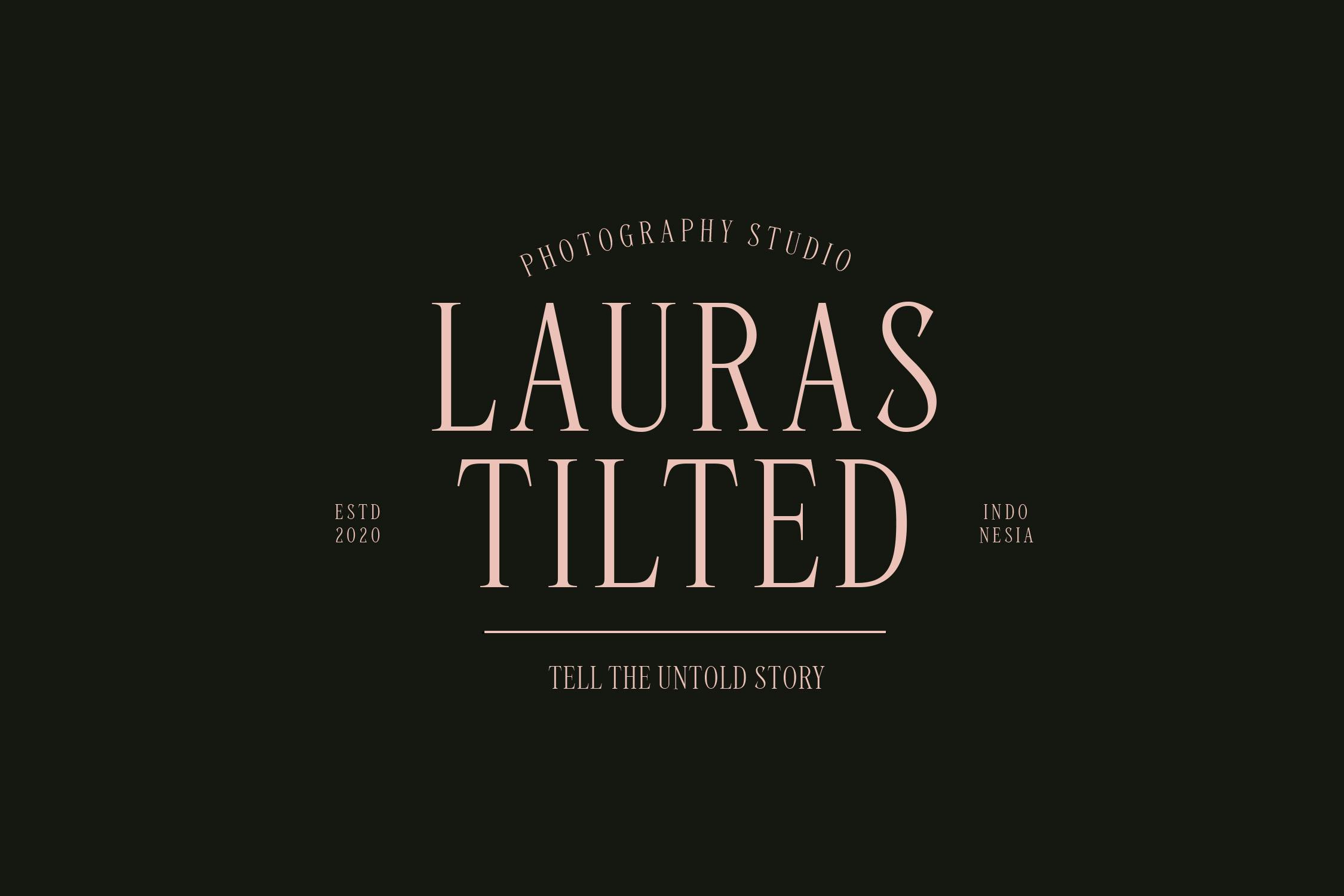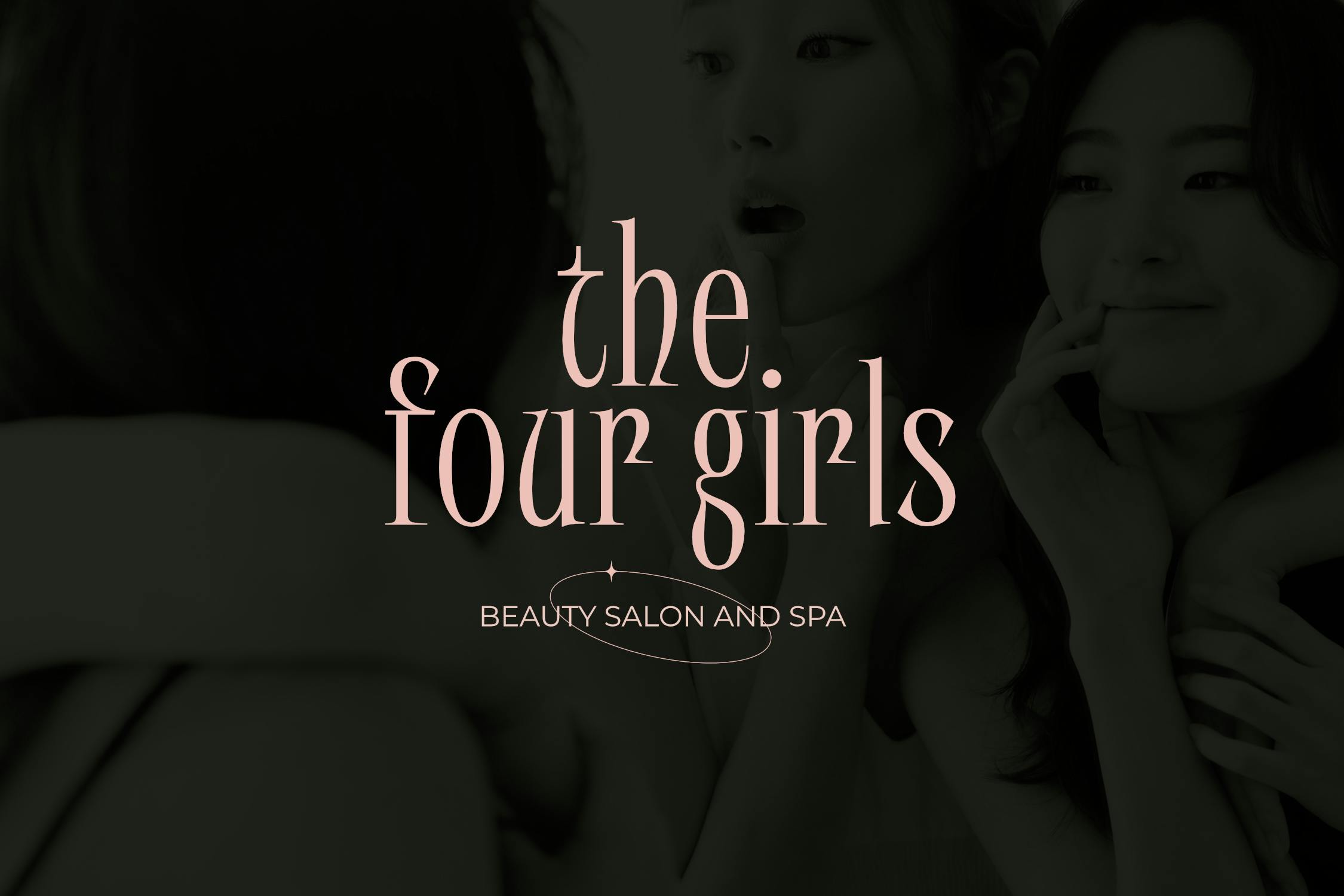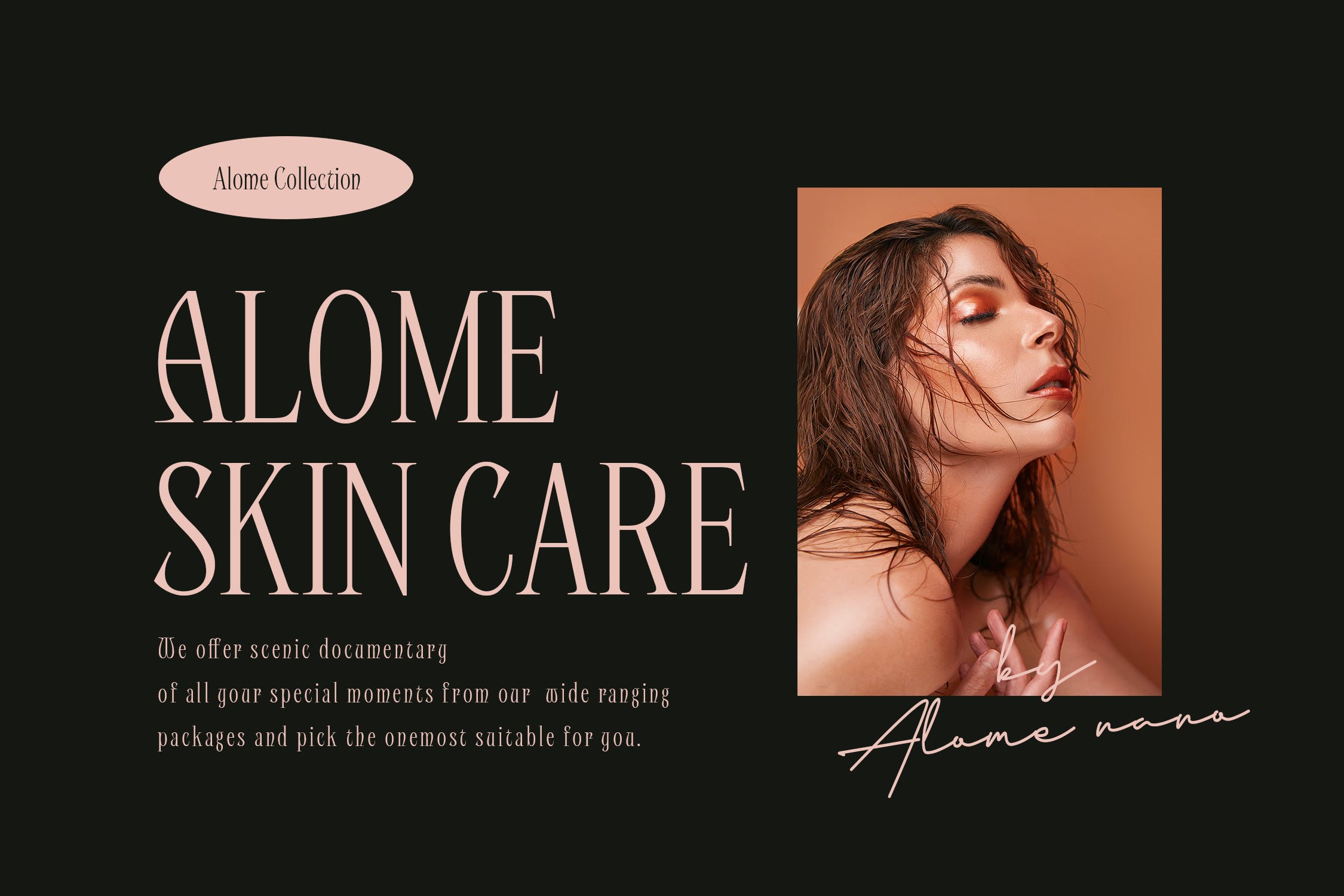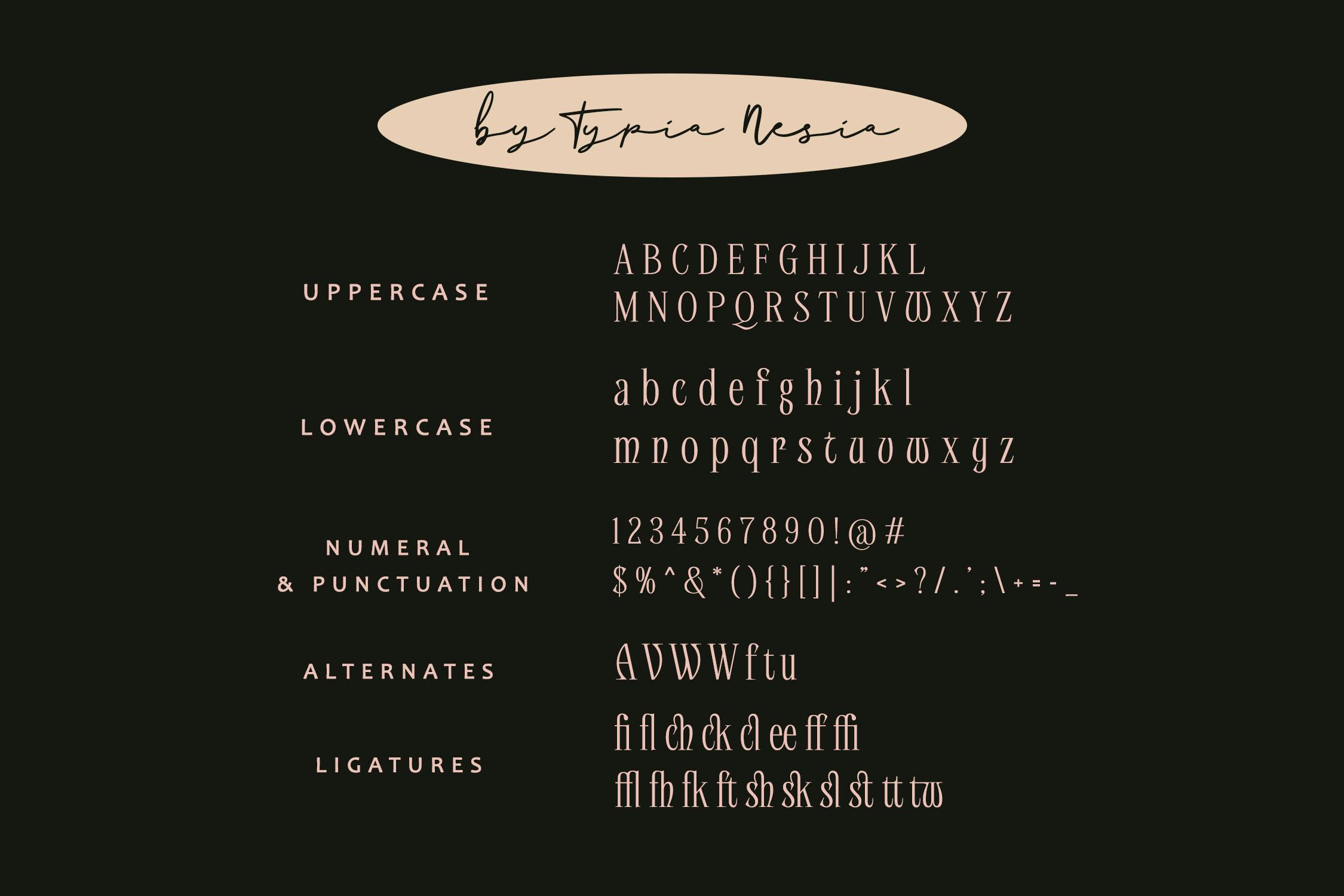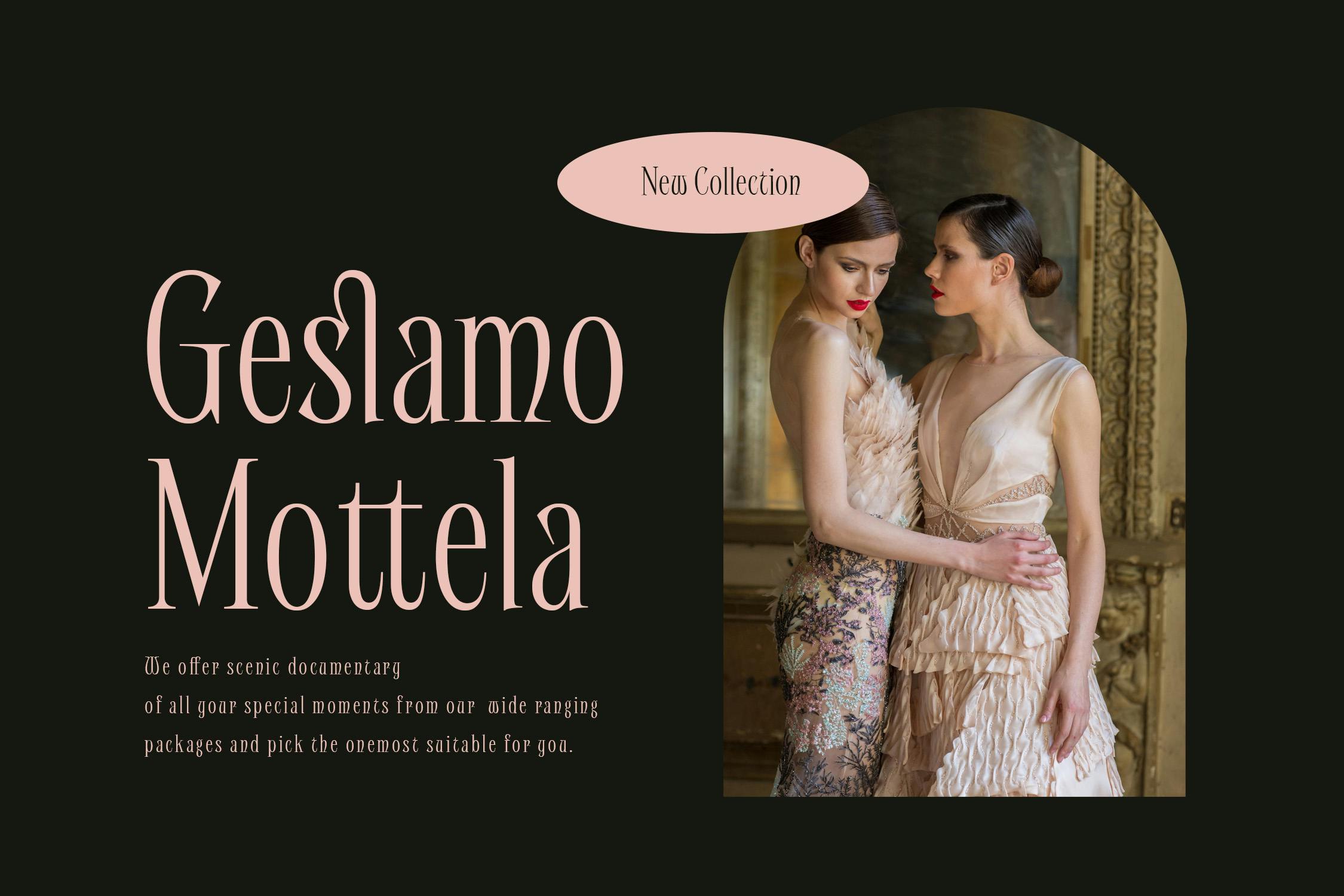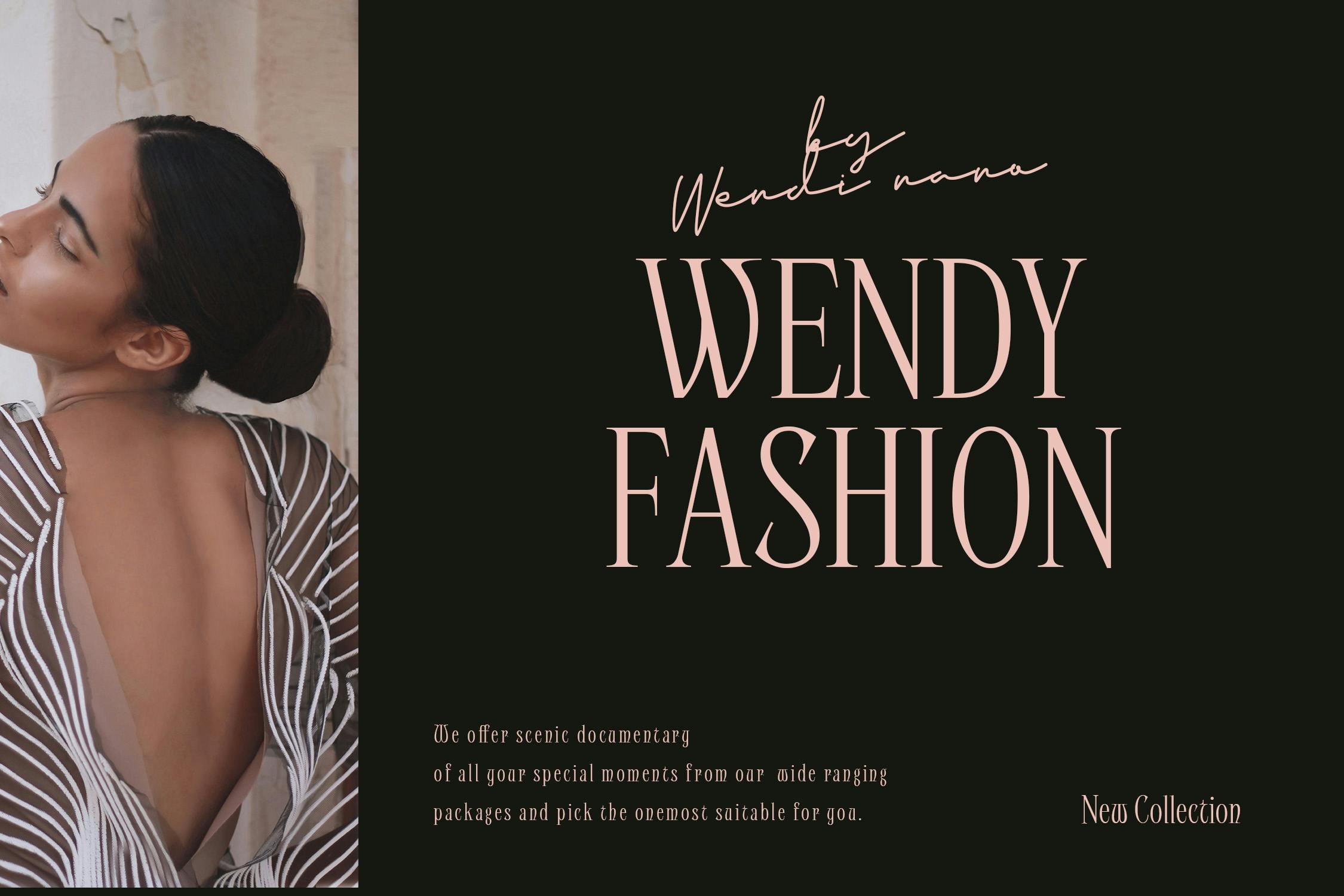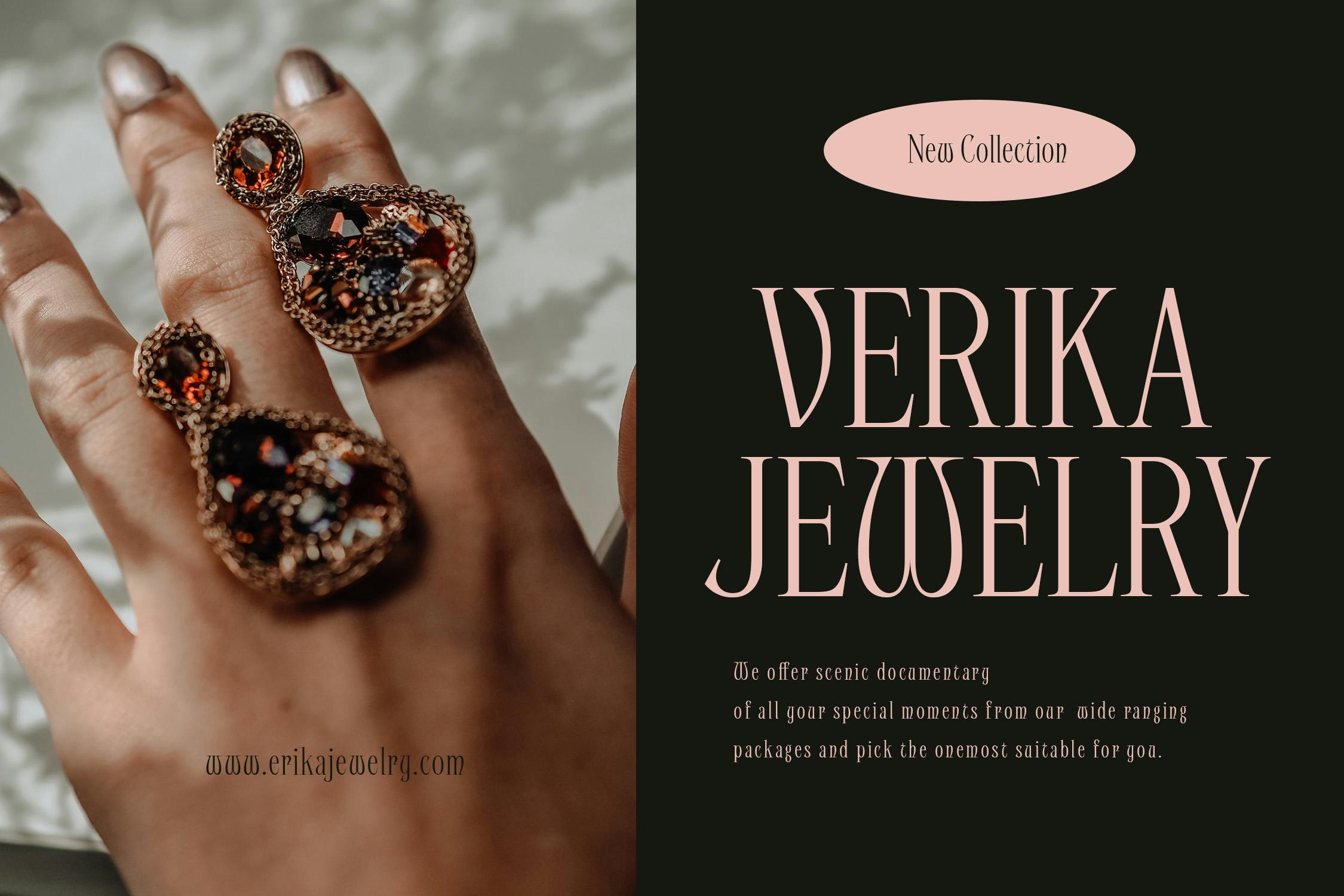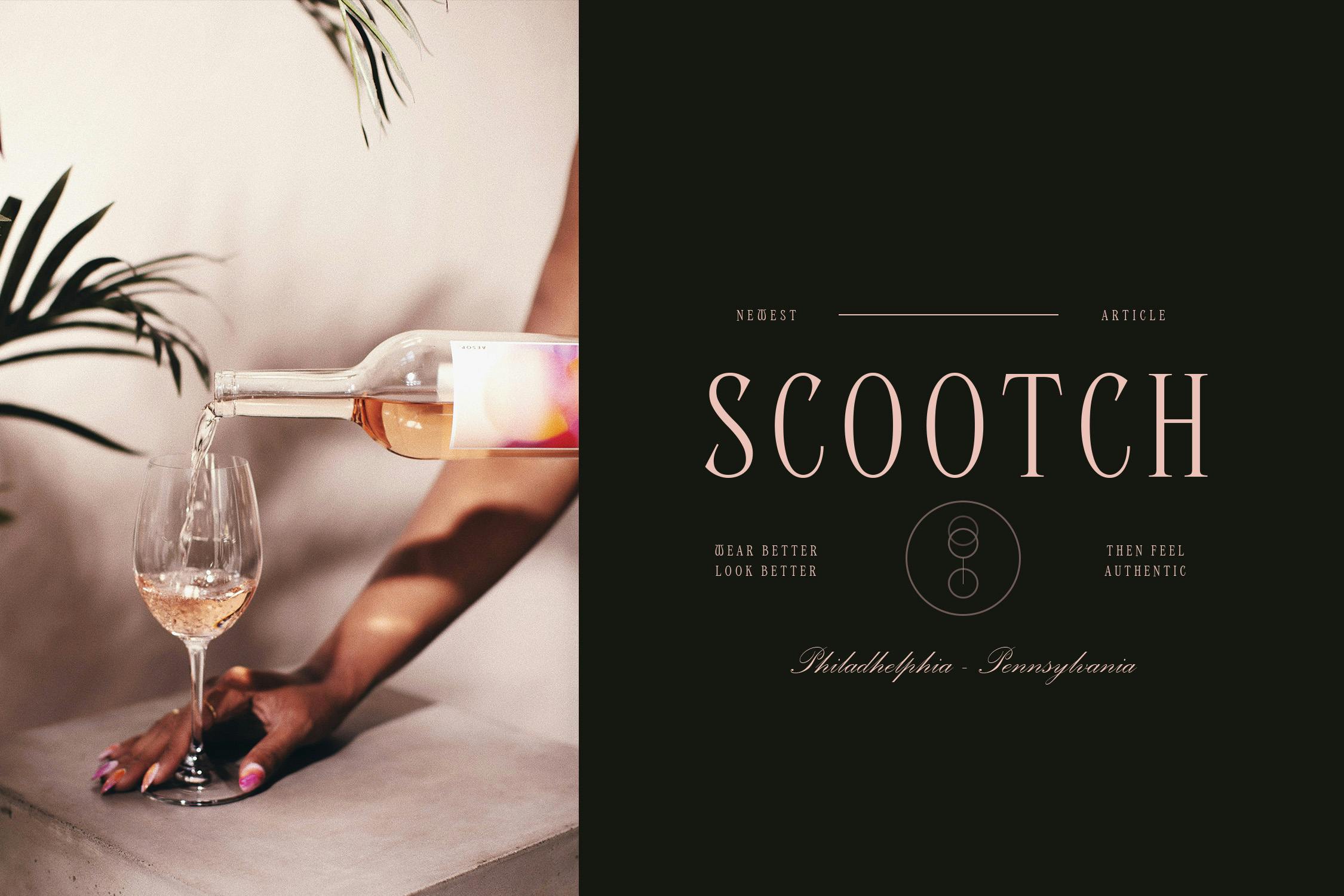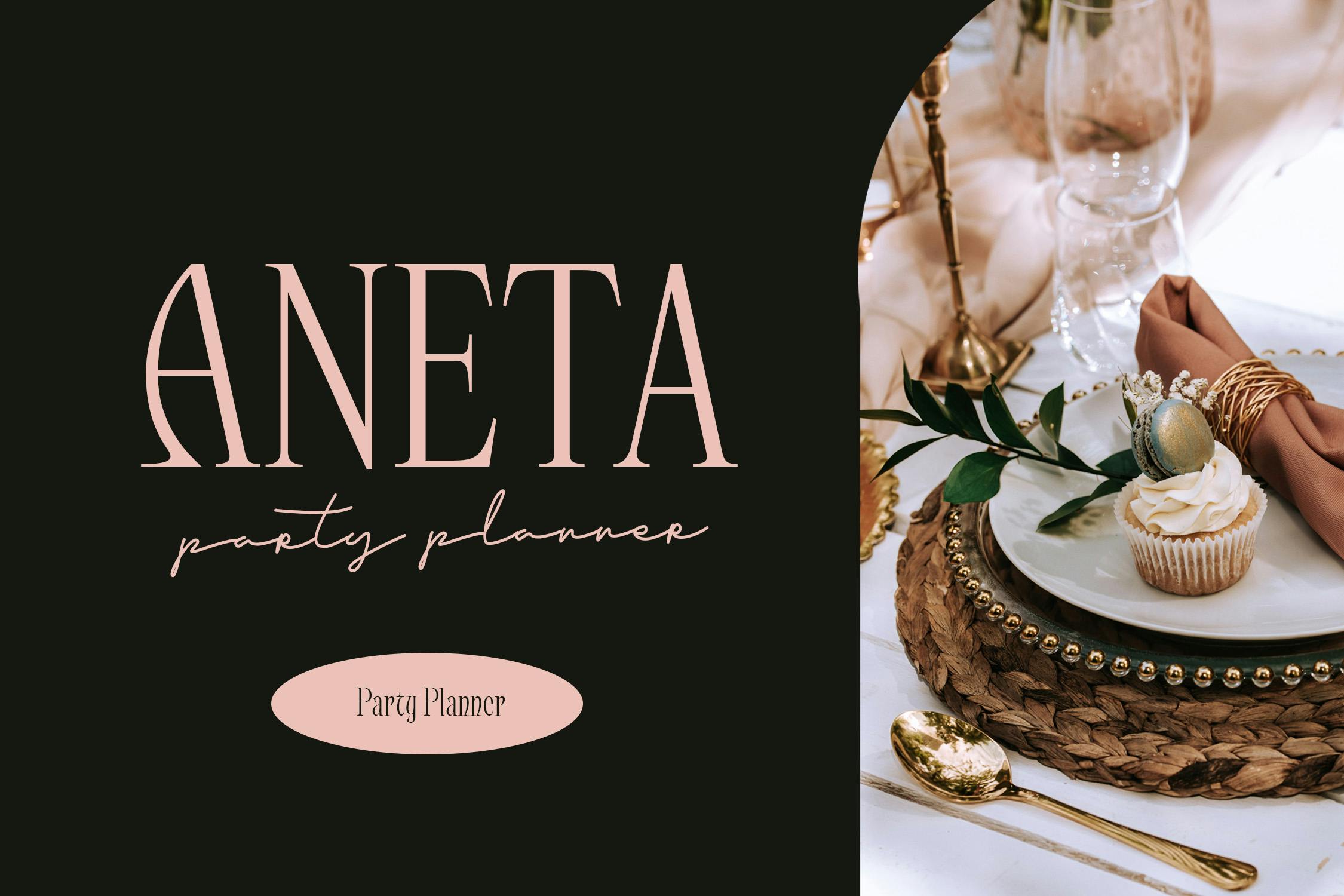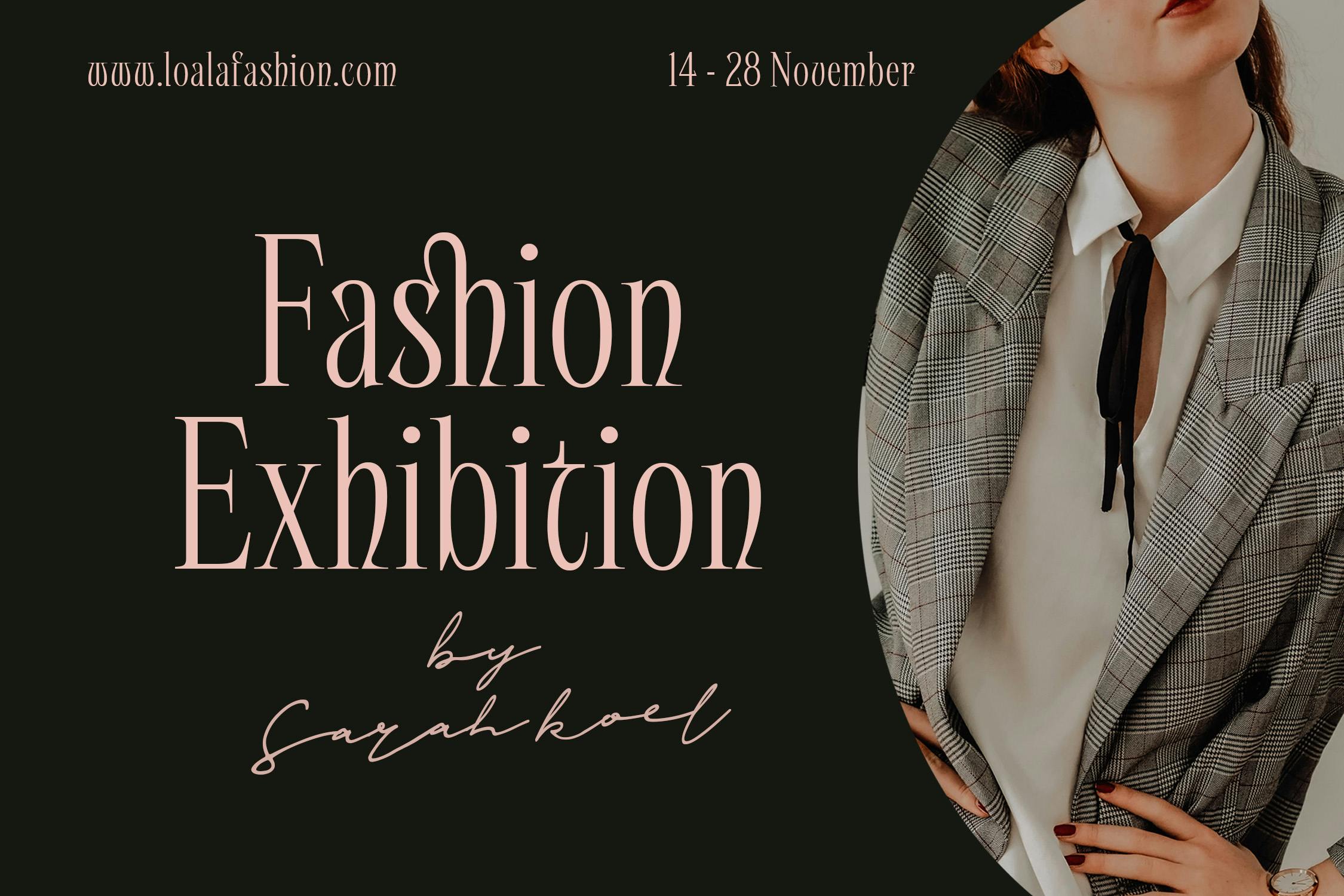
فونت Quietwave - فونت سریف لوکس و زیبا با طراحی کلاسیک و جذاب.
فونت Quietwave با برخی از جایگزینها و لیگاتورها ارائه میشود، بنابراین میتوانید آن را ترکیب کنید تا طراحی تایپوگرافی بینظیری ایجاد کنید. این فونت برای پروژههای آتی شما ایدهآل است، مانند طراحی لوگو و برندینگ لوکس، طراحی ویرایشگر کلاسیک، مجله زنانه، برند لوازم آرایشی، تبلیغات مد، برندینگ گالری هنری، موزه، آثار تاریخی و معماری، برندینگ بوتیک، طراحی ایستگاه، طراحی وبلاگ، تبلیغات مدرن، دعوتنامهها، نقلقولهای هنری، دکوراسیون منزل، عناوین کتاب/کاور و رویدادهای ویژه و بسیاری دیگر.